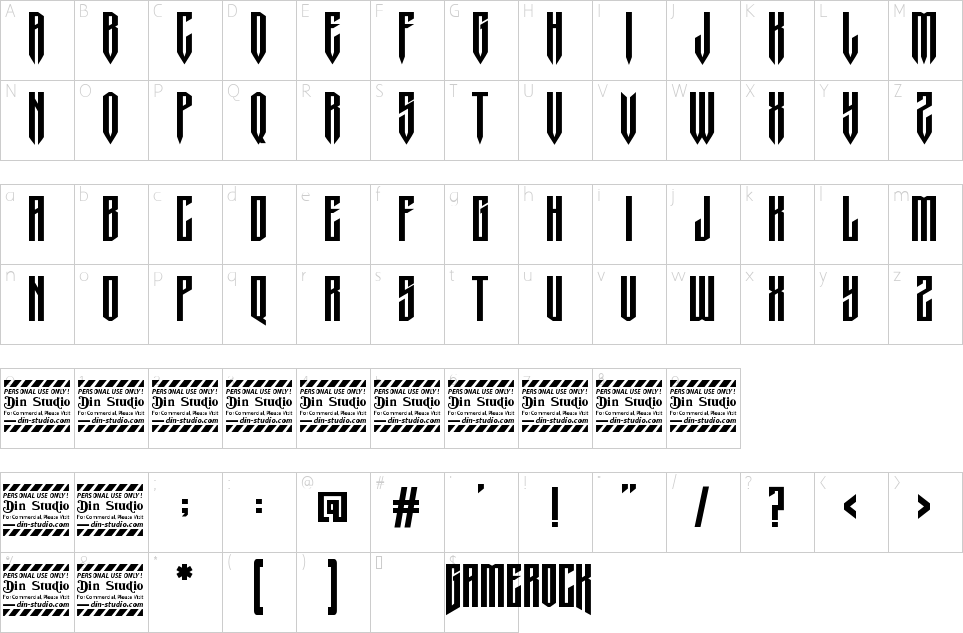
Gamerock Font – Download Grátis
A Gamerock é uma nova fonte de graça criada por Din Studio que oferece um estilo moderno e funcional, perfeito para ambientes digitais exigentes. Seja você um desenvolvedor web ou designer gráfico, essa fonte pode tornar seu trabalho mais eficiente e atraente. Download gratuito disponível tanto para Windows quanto para Mac, Gamerock foi descarregada mais de 20 mil vezes desde sua criação, demonstrando sua popularidade crescente. Ajudar você a criar conteúdo impactante é nossa prioridade, então não perca essa oportunidade de experimentar um design simples mas poderoso que irá destacar seu trabalho na web.